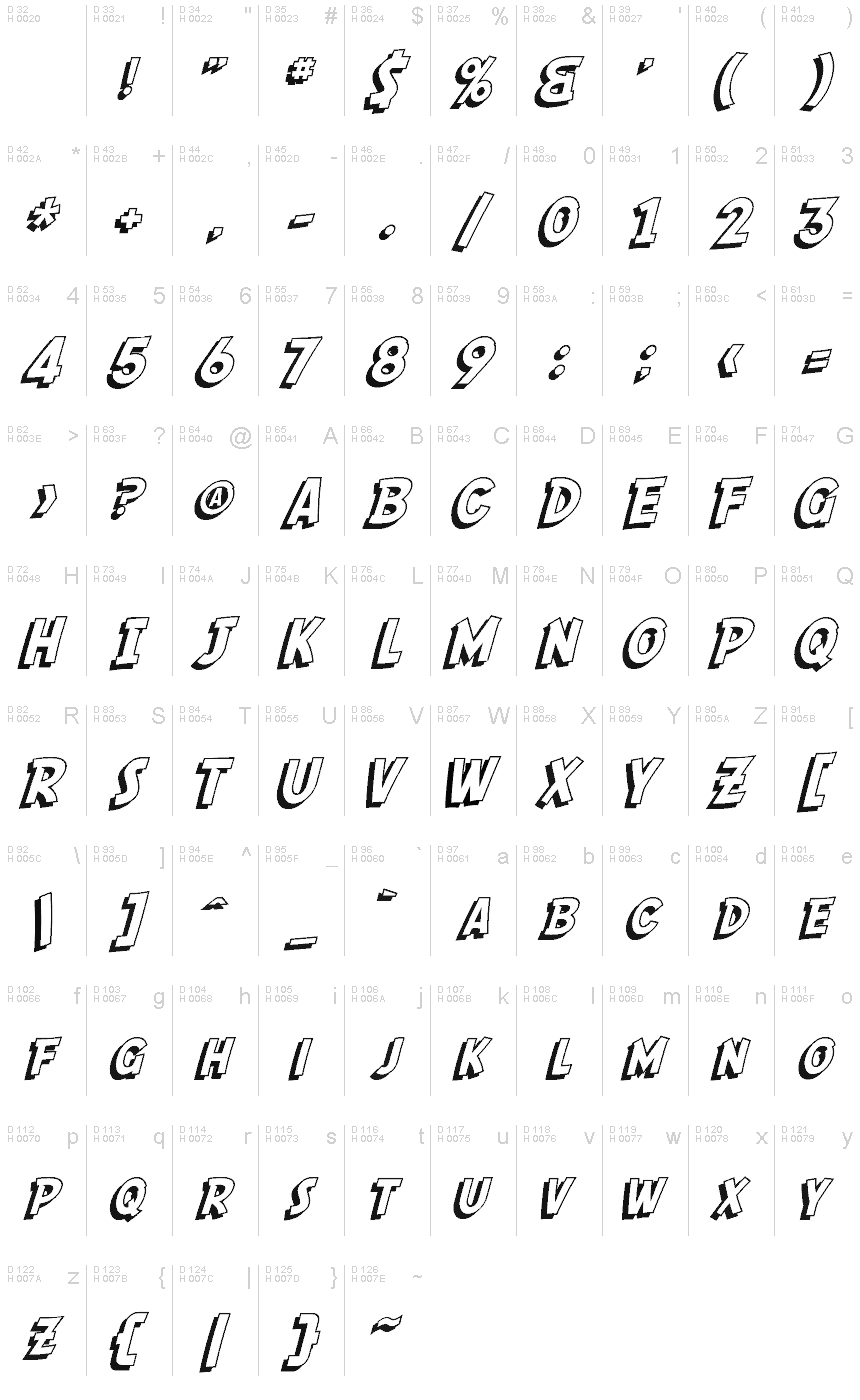
SF Comic Script Shaded wyrywa się ze strony swoją grubą, półskondensowaną strukturą, emanując ekspresyjnym stylem komiksowej sztuki. Stworzony przez ShyFonts Type Foundry, ten członek rodziny SF Comic Script wnosi do każdego projektu zabawny, a zarazem wyrazisty ton. Cieniowane detale dodają dynamicznego efektu trójwymiarowości, podkreślając jego charakter i sprawiając, że idealnie sprawdza się w zastosowaniach typu display, gdzie osobowość i czytelność są kluczowe.
Komiksowy styl tego kroju pisma doskonale odnajduje się w niezliczonych projektach kreatywnych – od powieści graficznych i animacji, po angażujące materiały marketingowe i przyciągający wzrok web design. Jego zdecydowana waga zapewnia czytelność, jednocześnie dodając osobowości nagłówkom i tytułom. Dla projektantów szukających fontu, który łączy siłę wizualną z nutą beztroski, SF Comic Script Shaded jest doskonałym wyborem, dzięki któremu Twój przekaz zostanie nie tylko zauważony, ale i poczuty.